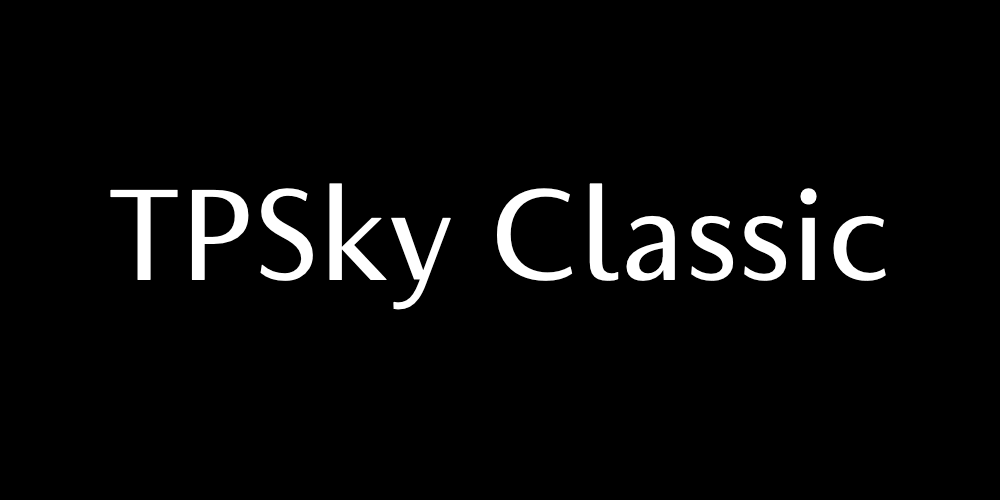
TPスカイ クラシック欧文開発ストーリー01「TPスカイ クラシックの特徴」
TPスカイ クラシックはサンセリフ体の簡潔明快さと、古典的な楷書の端正さを合わせ持つ書体です。和文の中に含まれる欧文として、開発当初は文字の形の相性が良いものを制作することだけ意識していました。しかし、制作と検証を重ね、形としての相性だけではなく、欧文においても古典的な骨格、トラヤヌス帝の碑文等に見られる大文字、オールドローマン系のスタイルをクラシックの典拠として位置付けています。
TPスカイ クラシック、ウェイト、コントラストの補間